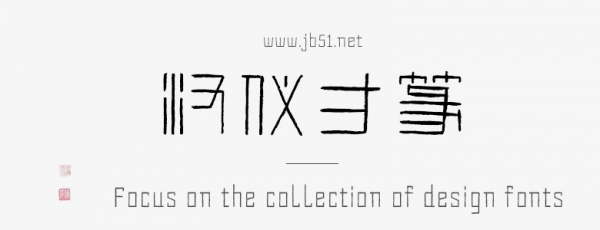
汉仪方篆U
汉仪方篆U由汉仪字库出品的艺术字体,不仅可以满足传统中式风格的印章排版需求,与其他书写字体搭配使用,还可以放大字形以展示篆书的装饰性,适合传统文化艺术和文博文旅等应用场景。有需要的朋友快来本站下载使用吧。
汉仪方篆U化圆为方,是谓方篆。汉仪方篆融合汉印缪篆的平方匀整、汉砖瓦当的朴拙浑厚以及铜镜铭的婉转流动,以现代设计手法重构传统金石文字,是篆书书写的一次创新尝试。字形端稳周正,笔画平直有力,线条可见金石刀笔的刚健遒劲,毛笔书写的质感正如篆印呈现于纸面。这款缪篆风格的书写字体气质古朴,适合传统文化艺术和文博文旅等应用场景。